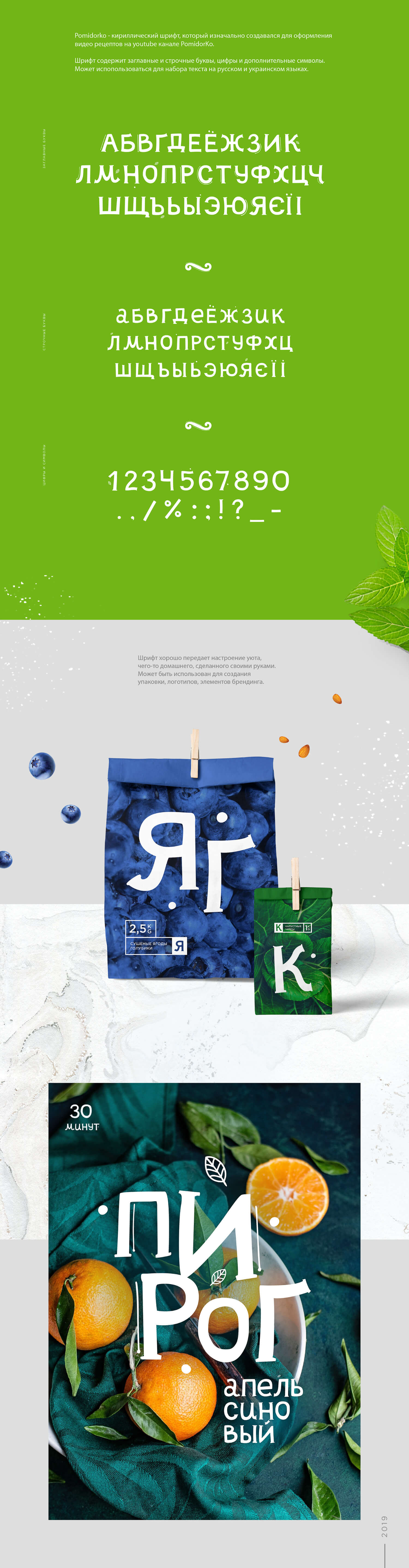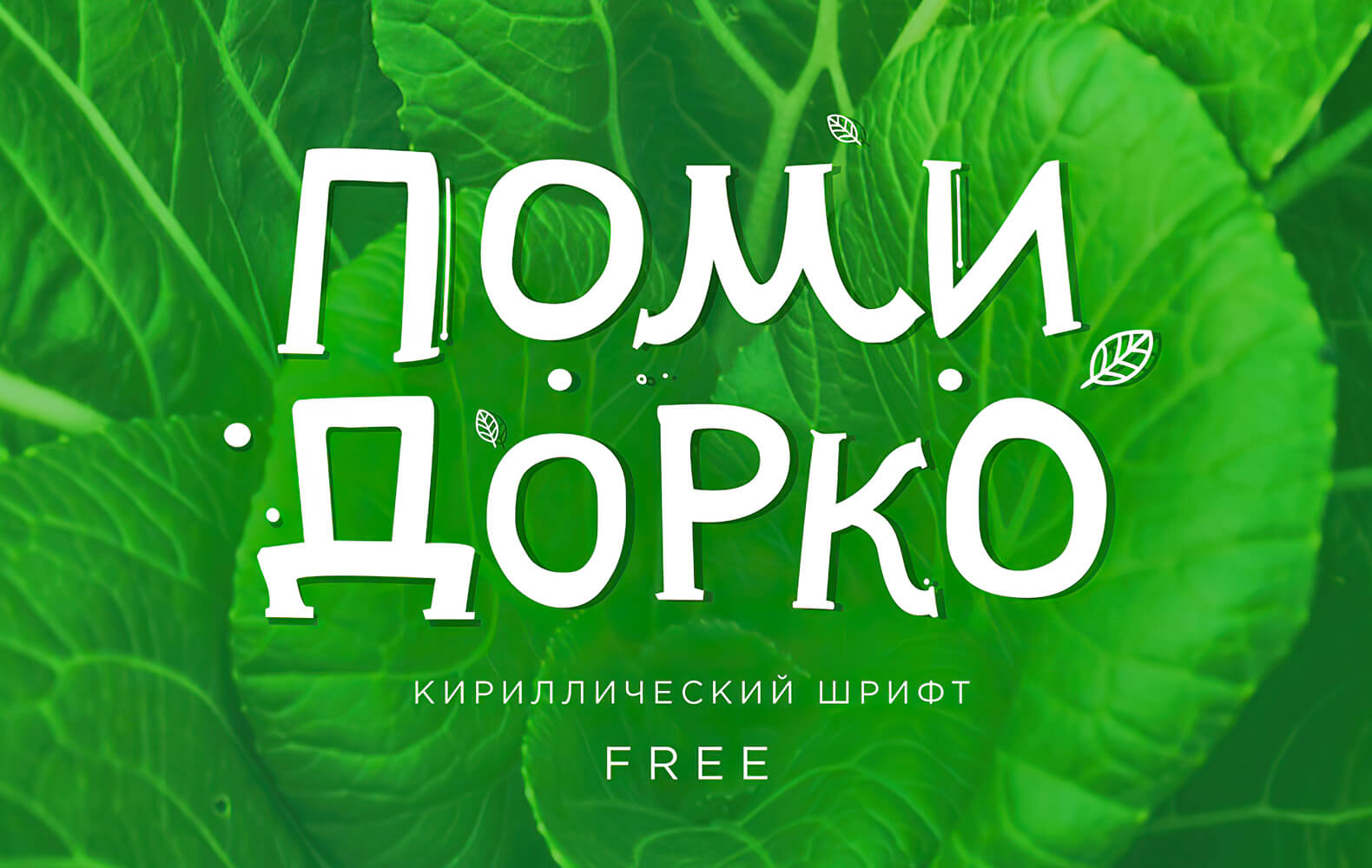
Шрифт - Помидорко (Кириллица)
Помидорко - кириллический шрифт, который хорошо передаёт настроение уюта и может быть использован для создания упаковки, логотипов, элементов брендинга.
Запятая у этого шрифта невзрачная и выглядит, как точка.
Weleri, сделайте её другим подходящим для вашего дизайна шрифтом.